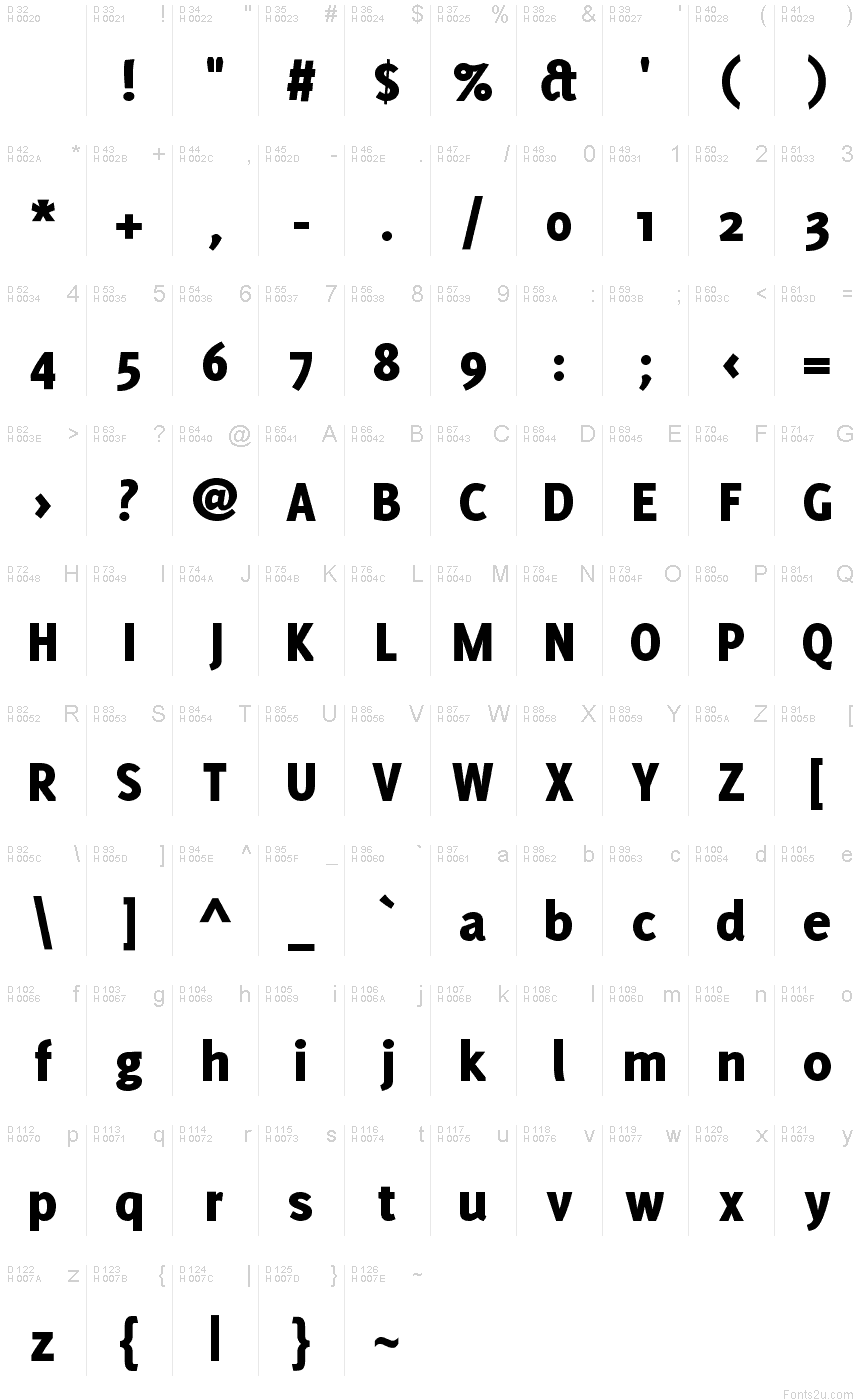
Delicious Heavy von Jos Buivenga ist eine kostenlose, schwere Sans-Serif mit breiten, soliden Buchstabenformen und kompakten Proportionen. Weiche Kurven lassen die dichten Striche zugänglich wirken, und scharf geschnittene Enden sorgen für eine dynamische Note.
Seine einfache, blockartige Silhouette harmoniert mit flachen Illustrationen und kräftigen geometrischen Formen auf Lebensmittelverpackungen, Kinderplakaten und der Markenidentität ungezwungener Restaurants. Bei Merchandising-Grafiken kann der Schriftzug eher Teil eines illustrierten Badges werden als als neutraler Text zu dienen.
Delicious Heavy